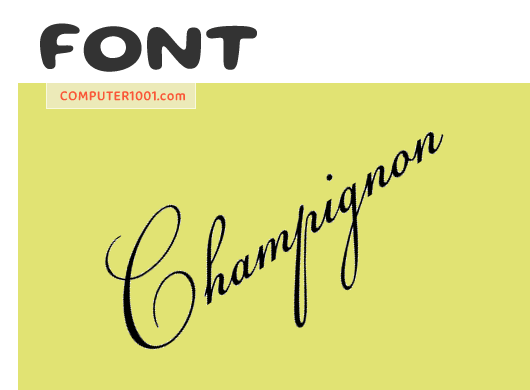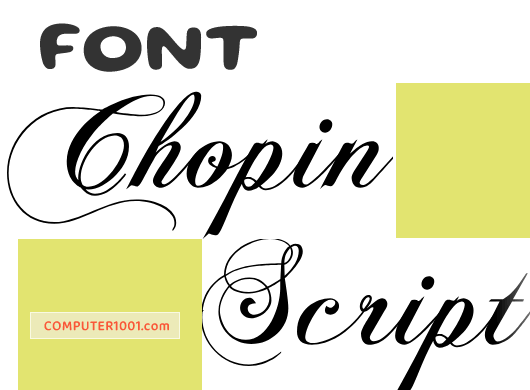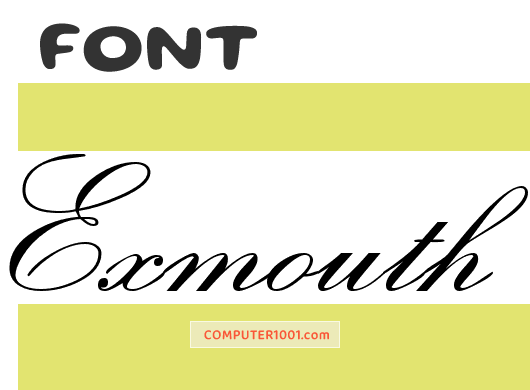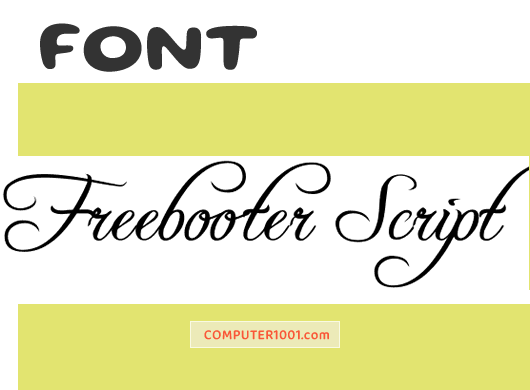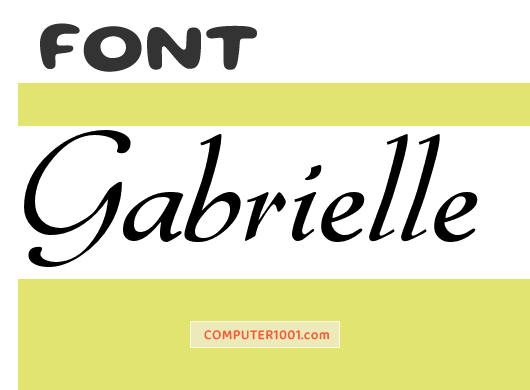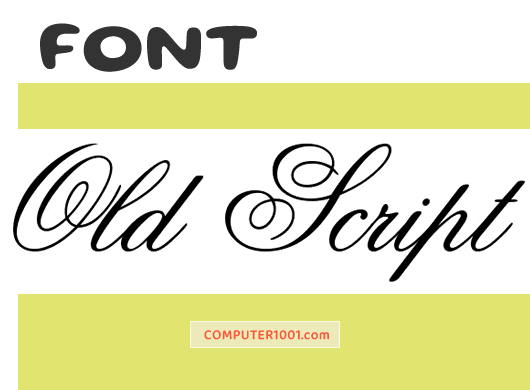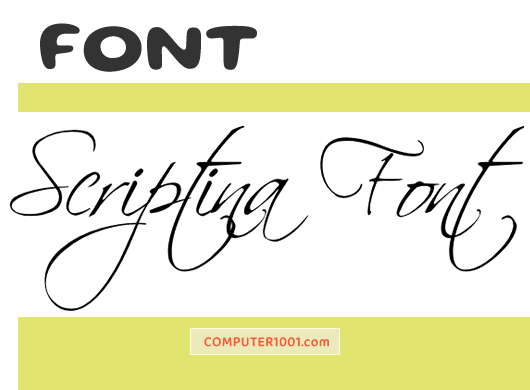
Berikut ini adalah 10 font kaligrafi (calligraphy) yang bisa di-download gratis.
Font yang termasuk Script typeface ini sering digunakan untuk desain logo, kartu ucapan, undangan pernikahan, dan lain-lain.
Font kaligrafi menyerupai tulisan tangan yang elegan. Font ini kelihatan seperti digambar dengan pena atau kuas; kadang-kadang juga memiliki tetesan, bercak dan ketidakteraturan yang menjadi ciri huruf-huruf yang digambar tangan.
Gayanya bervariasi, dari historis dan formal hingga edgy, whimsical, atau sentimental.
Font ini juga cocok untuk penulisan puisi dan peribahasa pendek di aplikasi Microsoft Word atau slides PowerPoint; serta desain poster, sampul buku, dan kemasan CD. Font tipe kaligrafi juga sangat bagus dijadikan sebagai huruf awal dekoratif untuk membuat aplikasi teks Anda kelihatan lebih spesial.
- Adorable
- Brandy Script
- Champignon
- Chopin Script
- English
- Exmouth
- Freebooter Script
- Gabrielle
- Old Script
- Scriptina